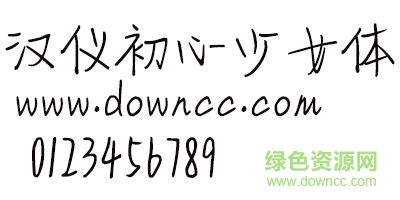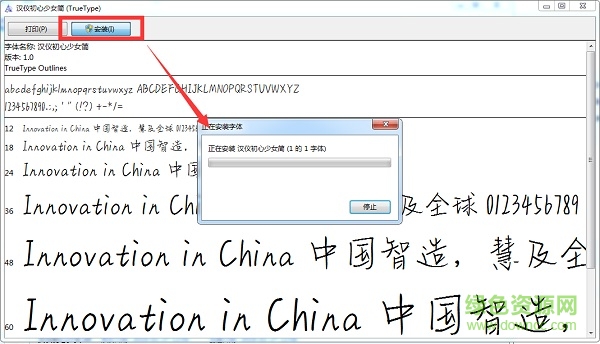
漢儀初心少女字體ttf是漢儀字體庫推出的一個(gè)女生版字體資源。小編為大家提供了這款字體字跡比較飄逸靈動(dòng),很受網(wǎng)友們的喜愛!這款字體在廣告設(shè)計(jì)上使用的比較多!
漢儀初心少女是一款可愛的字體,比較適合女孩子們使用,字體可愛至極十分秀氣??梢杂糜谟糜谄矫嬖O(shè)計(jì),支持中英文、數(shù)字輸入。讓人看了可以減輕壓力,精神放松,使人充滿活力!喜歡的用戶歡迎在綠色資源網(wǎng)下載。